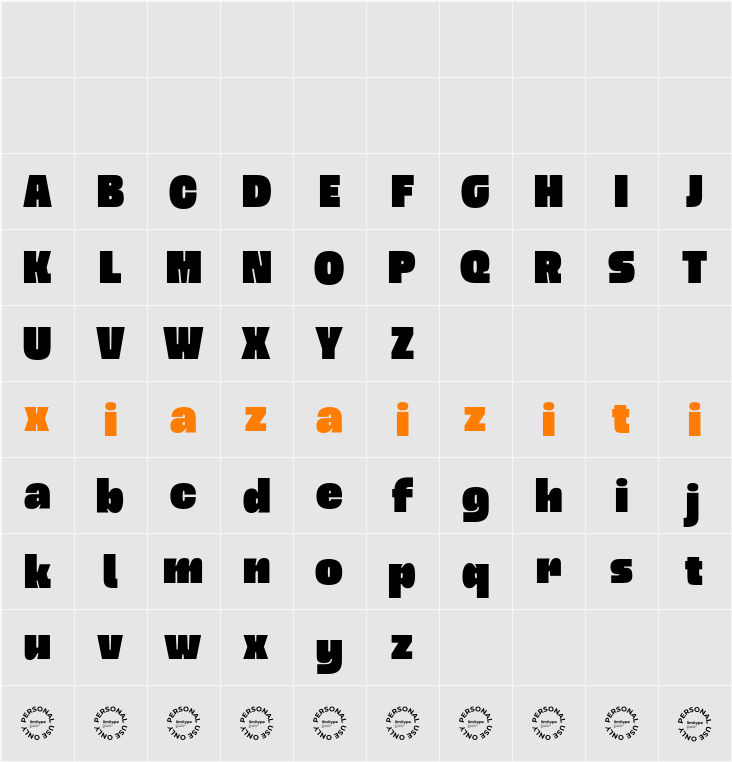
Wosker Demo
Wosker Demo,这款字体结构工整、笔画清晰,兼顾美观与易读性,适用于标题、正文、海报、包装、LOGO 等多种场景。字形优雅稳定,风格百搭耐看,适配日常排版与创意设计,让文字呈现更舒适、更具质感。Wosker Demo一笔一画,皆是细节,以均衡的比例、流畅的线条打造舒适视觉体验,字形端正大气,风格简约现代。无论是商业设计、品牌宣传还是日常排版,都能轻松驾驭,让文字更有格调与力量。Wosker Demo字体下载。
• 设计师: Muhammad Muammar